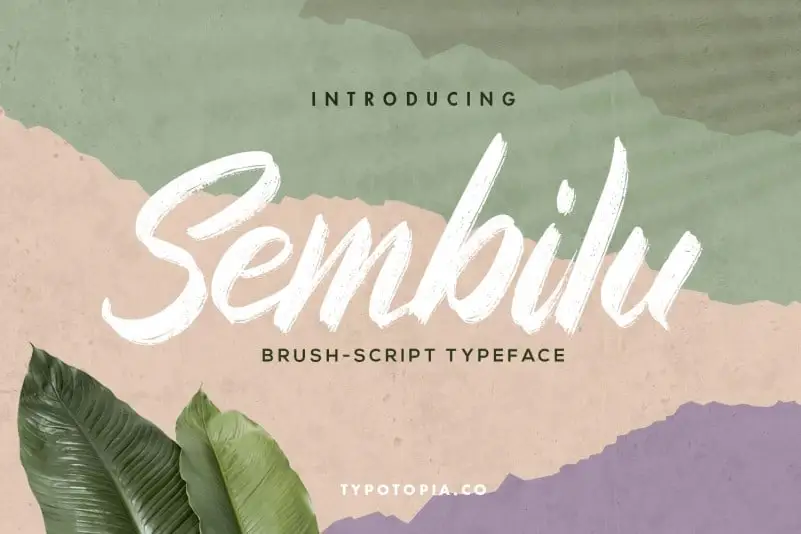
Sembilu Brush-Script Font – Download Grátis
Introduzimos Sembilu Brush Font, uma tipografia Brush-Script que se destaca por sua elegância e versatilidade. Essa fonte foi criada para abrangências variadas dos mais comuns, como logos, panfletos de propaganda, embalagens, cartões de visita, etc., até aos menos óbvios, como livros e cartas de convite. Se você busca uma fonte que não apenas atenda ao seu gosto pessoal, mas também à sua necessidade profissional, Sembilu Brush Font é a escolha certa. Seja para criar um logo inovador ou fazer uma propaganda impecável em revistas, nossa tipografia pode ser o elemento final que transformará sua ideia em obra-prima visual. Sua característica principal de estilo Brush-Script permite-lhe expressar uma personalidade única e moderna em qualquer formato. Este tipo de fonte é perfeito para criar um impacto no design gráfico de nível superior, seja você um designer ou artista visual, pois oferece o que há de melhor na tipografia. Na era digital onde tudo se move rápido e está sempre em movimento, uma fonte como a Sembilu Brush Font pode fazer toda a diferença. Seja para personalizar suas mensagens digitais, criar design gráfico impecável ou simplesmente dar vida à sua ideia artística, o Sembilu Brush Font tem você de corpo e alma.